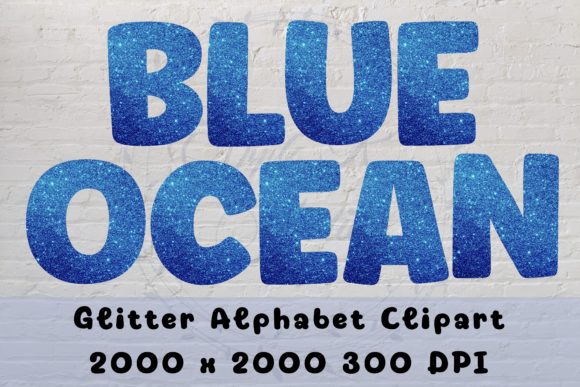
Blue Ocean Glitter Alphabet Clipart
Jika anda sedang mencari aset berkualiti tinggi seperti Blue Ocean Glitter Alphabet Clipart, pakej premium ini merupakan pilihan yang hebat untuk projek kreatif anda.
Dicipta dengan ketepatan, Blue Ocean Glitter Alphabet Clipart menyediakan vektor yang bersih, tipografi yang licin dan lesen komersial untuk ketenangan fikiran.
Sama ada anda mencipta produk POD (Print on Demand), jemputan perkahwinan atau grafik media sosial, Blue Ocean Glitter Alphabet Clipart amat bersesuaian.